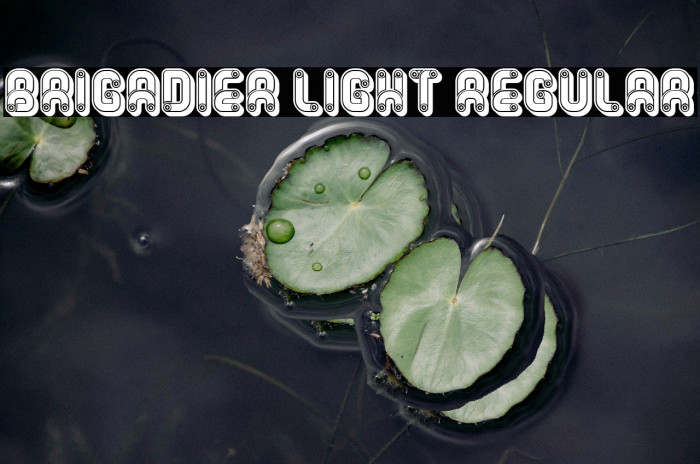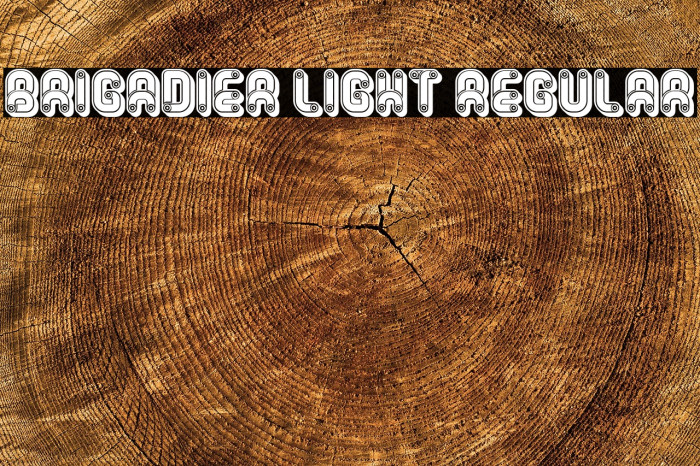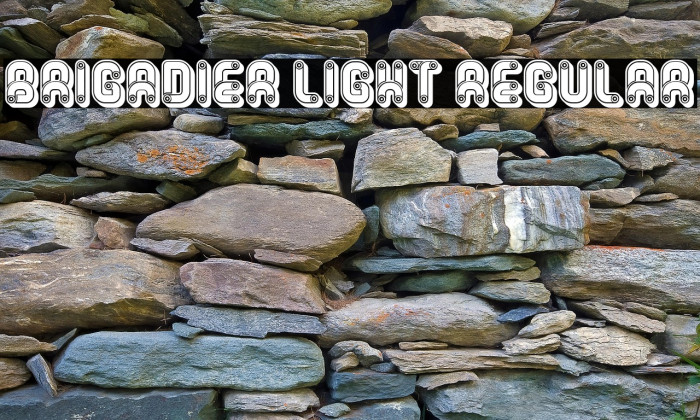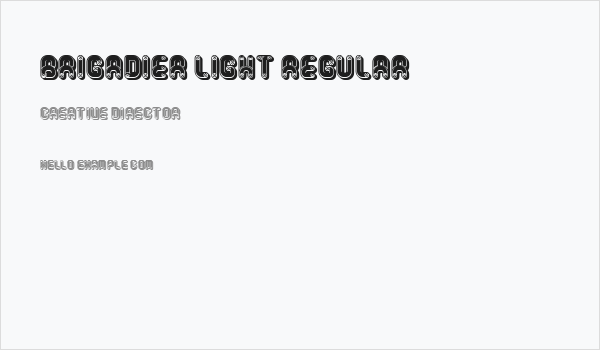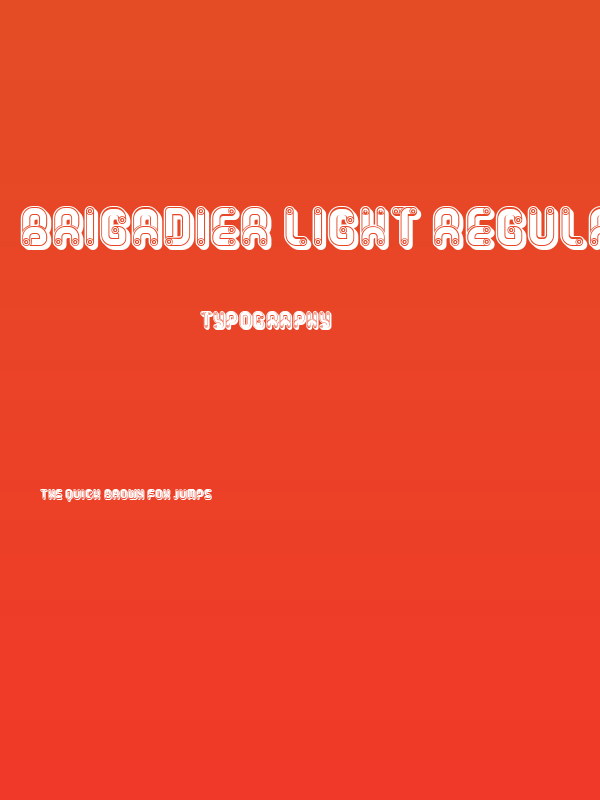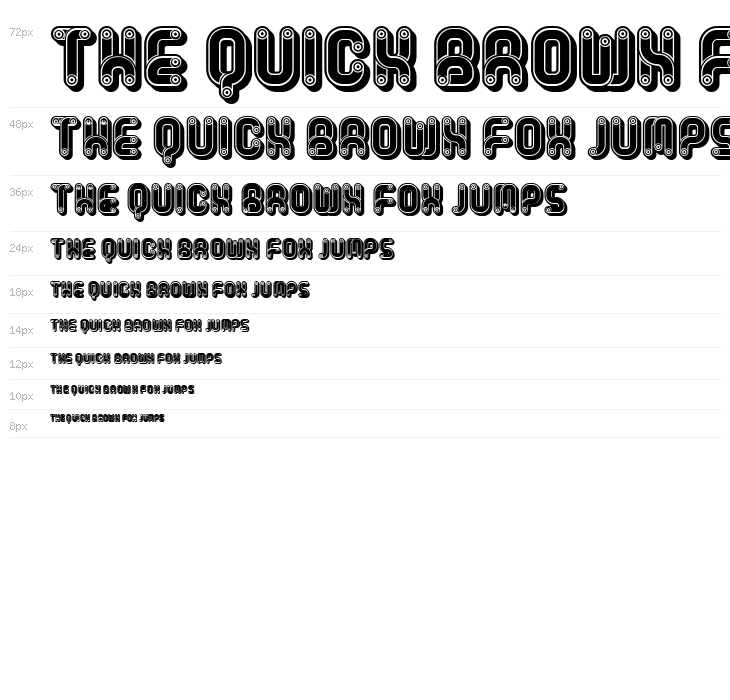
Brigadier Light Regular Font
| Stile generale | Futuristic, Industrial |
| Progetti proposti | Ideal for technology branding, futuristic posters, industrial-themed designs, and innovative product packaging. |